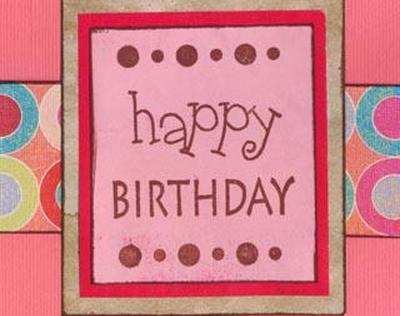
Шрифты для резиновых штампов — универсальный инструмент для всех, кто интересуется изготовлением открыток и другими поделками из бумаги.
Доступные варианты шрифтов
Наборы штампов с буквами алфавита представлены в различных вариантах шрифтов. Например:
- Засечки : Шрифты с засечками — это шрифты с небольшими архитектурными деталями по краям букв. Times New Roman — это шрифт с засечками.
- Без засечек : шрифты без засечек представляют собой простые печатные буквы без дополнительных украшений. Arial — пример популярного шрифта без засечек.
- Скрипт : скриптовые шрифты выглядят как рукописный текст. Некоторые скриптовые шрифты имеют очень формальный вид, в то время как другие гораздо более случайны.
- Декоративные : декоративные шрифты — это шрифты, которые явно не подходят ни к какой другой категории. Их лучше всего использовать для заголовков и заголовков, так как витиеватые детали декоративных шрифтов могут быть трудночитаемыми.
Деревянное крепление против прозрачного акрила
После того, как вы определились с типом шрифта, который хотите приобрести, вам нужно будет выбрать между наборами штампов из дерева и акрила. Деревянные штампы — это то, о чем думает большинство людей, когда слышат термин «штамповка». Штампы на деревянных панелях являются фаворитом мастеров, так как они создают очень детализированные изображения. Каждая буква в алфавитном наборе закреплена на отдельном блоке, а наверху блока напечатана направляющая, которая поможет вам равномерно выровнять текст.
Прозрачные акриловые штампы продаются на тонком пластиковом листе. Перед использованием их необходимо установить на чистый блок. Прозрачные акриловые штампы — отличный выбор для печати текста, так как вы можете легко увидеть положение отдельных букв. Марки также занимают гораздо меньше места в вашей мастерской, поскольку для каждой буквы используется одно и то же крепление.
Печать четкого изображения
Для начинающих мастеров штамповка четких изображений — сложная задача. Нет ничего более разочаровывающего, чем покупка нового набора штампов с алфавитом только для того, чтобы обнаружить, что вы штампуете неразборчивый текст. Чтобы штамповать четкое изображение, помните следующие советы :
- Чтобы не ошибиться с незаменимым проектом, сначала потренируйтесь штамповать на бумаге для заметок. Это даст вам возможность убедиться, что вы правильно владеете техникой и размещением букв.
- При нанесении чернил на штамп с алфавитом поместите штамп на плоской поверхности изображением вверх и нанесите чернила слева направо. Этот метод предотвратит чрезмерное нанесение чернил — частую причину размытого текста.
- При штамповке изображения держите штамп за стороны и нажимайте посередине. Не раскачивайте штамп вперед и назад.
- Если вы видите маленькие отметки по краям букв, возможно, ваш набор штампов обрезан неправильно. Острым ножом срежьте лишний материал.
Штампованные компьютерные шрифты
Хотя штамповка резины может быть очень интересной, иногда просто удобнее использовать компьютерный шрифт, имитирующий текст с резиновым штампом. Если вы ищете бесплатные компьютерные шрифты с резиновым штампом, обратите внимание на эти отличные варианты;
- Rubberstamp — необычный и уникальный шрифт, который выглядит как буквы пишущей машинки, слегка смещенные по центру.
- Mailart Rubberstamp — это бесплатный шрифт со свежим и современным дизайном.
- Stamped — это шрифт в стиле гранж, имитирующий буквы с резиновым штампом. Однако доступны только прописные буквы.
- Rub Это слегка шероховатый шрифт, который включает как прописные, так и строчные буквы.